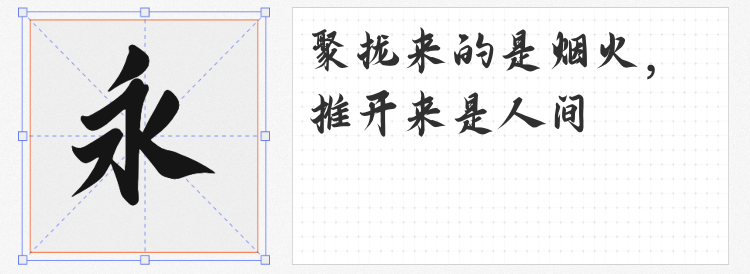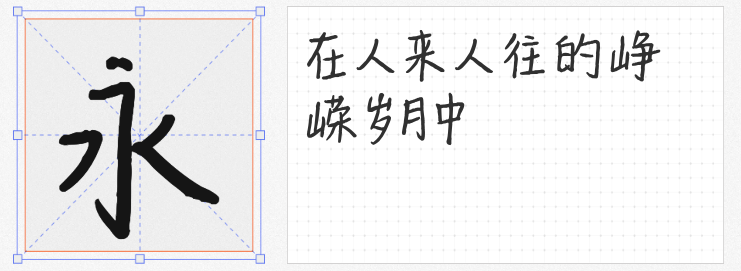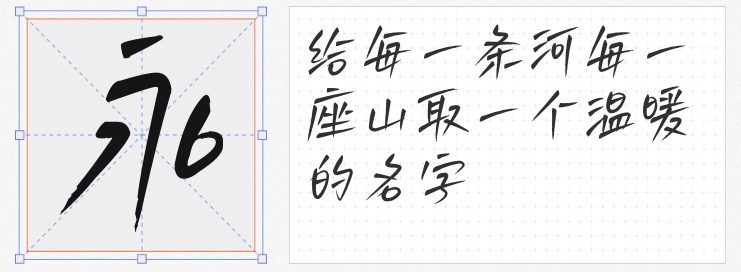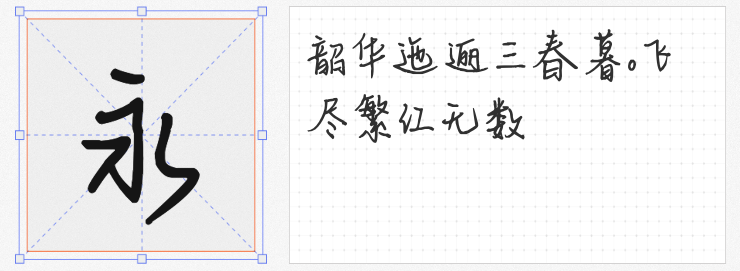
在追求设计个性化的今天,手写字体凭借其独特的情感表达与人文气息,成为设计师们的“秘密武器”。今天为大家精选4款免费商用的手写字体,涵盖艺术、文艺、怀旧等多种风格,助你轻松打造吸睛设计!
平方韶华体以流畅的笔触与适中的粗细变化,营造出兼具力量感与柔美感的视觉效果。其字形结构舒展大气,笔画转折处自然灵动,既保留了手写的温度,又具备现代设计的简洁感。无论是海报标题、品牌LOGO,还是网页Banner,都能瞬间抓住观众眼球。书法爱好者还可将其用于字帖临摹,感受传统与现代的碰撞之美。
若你偏爱清新文艺风,平方时光体将是你的不二之选。这款字体笔触自然均匀,字形端庄清秀,仿佛自带时光滤镜,为文字注入静谧的诗意。它尤其适合日记、手账、书信等私密场景,让文字如手写般温暖;在海报标题、文案排版中,也能轻松营造文艺氛围,让设计更具故事感。
为纪念重庆“山城棒棒军”这一即将消失的职业,这款字体以粗犷的笔触还原了棒棒们肩扛重担、步履坚定的身影。字形古朴厚重,充满力量感,虽无英文与数字编码,却能通过纯中文排版传递出独特的城市文化底蕴。适用于文化海报、纪录片字幕、地域特色设计,唤醒人们对传统职业的敬意与回忆。
由山人白路亲手创作的这款字体,以6796个字符的丰富性,覆盖中文、英文、数字及标点符号,满足多样化设计需求。其风格清新俏皮,笔触轻盈灵动,既保留了手写的随性,又融入了现代设计的精致感。无论是品牌包装、社交媒体图文,还是文艺风海报,都能为设计增添一抹灵动的青春气息。
这4款免费商用字体,既有艺术感爆棚的视觉冲击,也有文艺清新的情感表达,更有致敬传统的文化情怀。无论是商业设计还是个人创作,它们都能让你的作品脱颖而出。赶快收藏下载,让这些充满温度的手写字体,为你的设计注入灵魂吧!